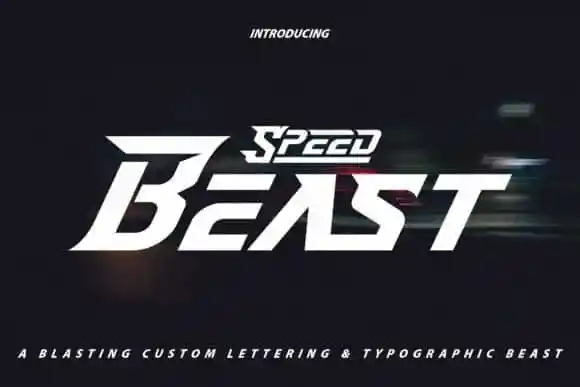
Speed Beast Display Font – Download Grátis
A Speed Beast Display Font é uma tipografia display futurista projetada para headlines que captura exatamente a essência do voo rápido e da velocidade. Ela foi criada por Vunira, um designer de fontes, e seu desenho fluido e arredondado transmite um impacto poderoso em qualquer design que ele compreenda, seja para assuntos relacionados à jogos ou esportes. A fonte também se destaca perfeitamente como uma logo sozinha em designs minimalistas, como nomes de marca e taglines. Ela é ideal tanto para ambientes gaming quanto para temas desportivos, garantindo um visual atraente e moderno. Com certeza, a Speed Beast Display Font será uma escolha inteligente para quem busca uma fonte display que represente velocidade e agilidade com precisão e estilo.